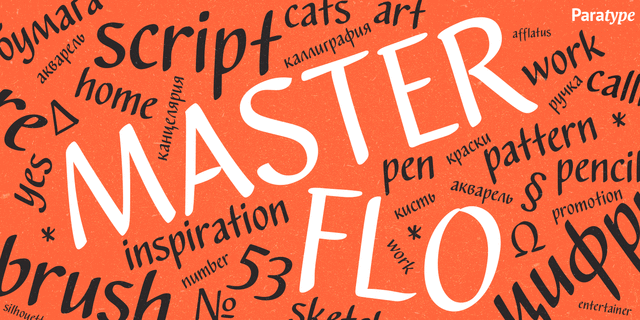
Оригинальный акцидентный шрифт свободного рисунка, построенный на основе рукописного оригинала. Разработан для компании ПараТайп дизайнером Натальей Васильевой в 2007 году. Имитирует письмо ширококонечным фломастером или плоской кистью. Предназначен для коротких текстов и заголовков неформального стиля.
художественный, гармоничный, приятный, уютный, комфортный, дружелюбный, добрый, вежливый, спокойный, традиционный, культурный, благородный, интеллигентный, образованный, красивый, аккуратный, оптимистичный, мягкий, неторопливый, милый, мультяшный, семейный, праздничный, домашний, симпатичный, мирный, удобный